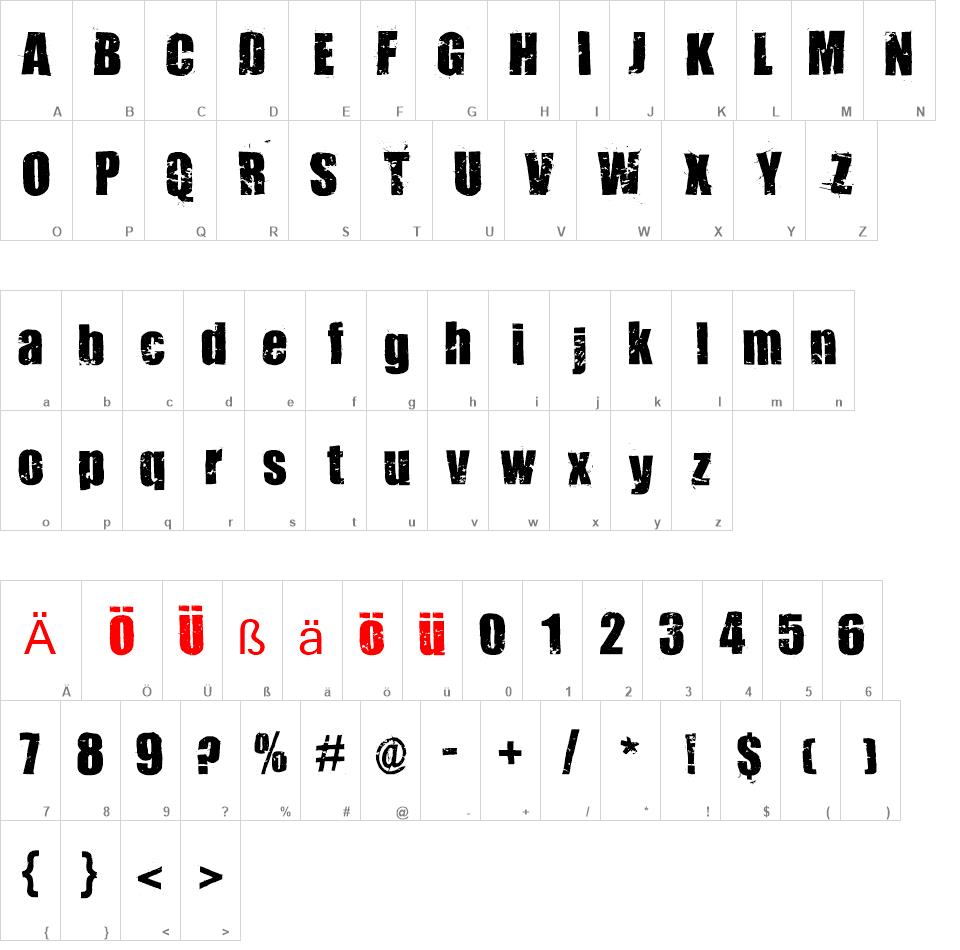
321 impact
321 impact font
321 impact eskitme Türkische Schrift wird als gefährlicher Nachrichtentitel in Nachrichtenbannern bevorzugt. Türkische Zeichen sind kompatibel. 321 Auswirkungen herunterladen.